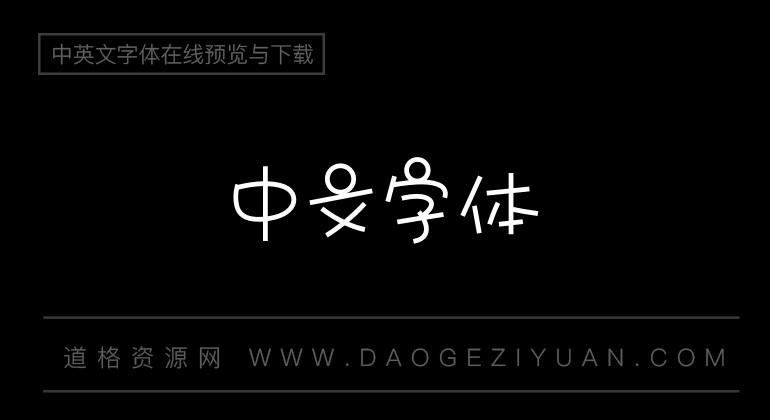
二字元滚滚熊猫简常规字体是一种比较简单的中文字体,它只有两个字符,即“滚”和“熊”,没有任何复杂的笔画。它的特点是字体简洁、细腻,笔画简单、清晰,易于辨认,适合大量文字的排版。它可以与其他字体混排,也可以单独使用,是一种非常适合文字排版的字体。文件名:ACGN-QPandaGB-Regular-2.otf
二字元滚滚熊猫简 常规是一款非常不错的手写艺术字体,具有很好的视觉感,适合于文化类的宣传设计、商业类品牌的广告和产品包装设计以及个性化文字排版等较多场景。